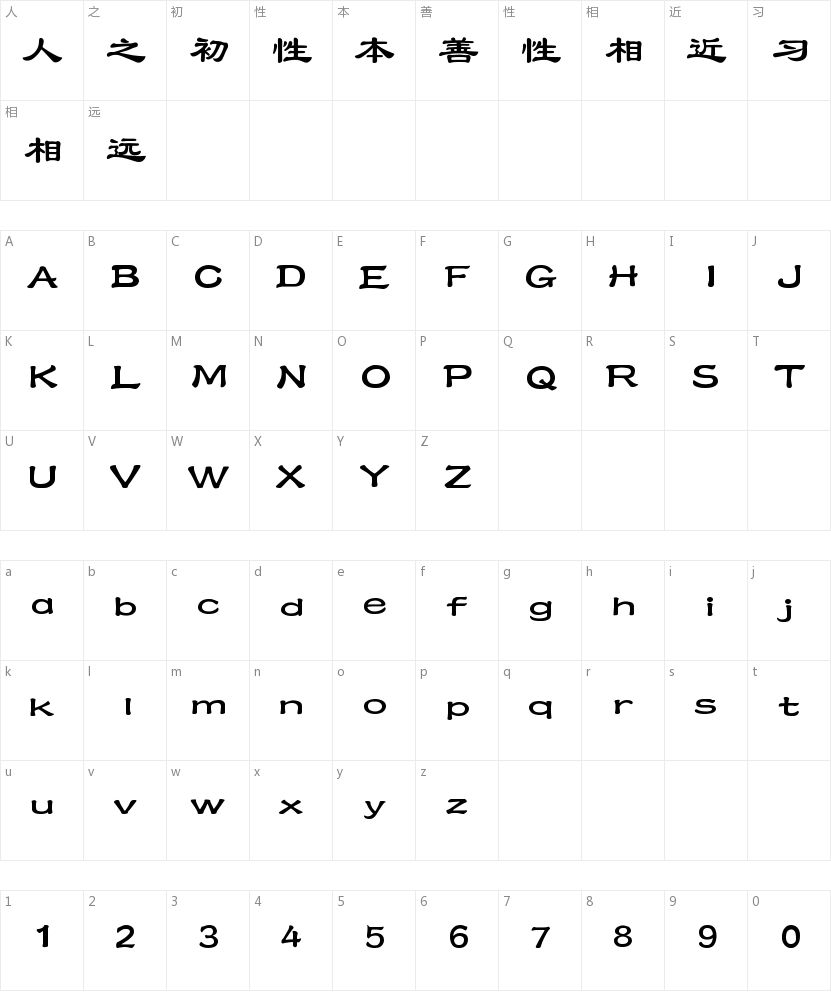
长城粗隶书体
长城粗隶书体是一种中国古典书法字体,它源于宋代宋体,是一种比较粗糙的字体。字体特点是笔画比较粗,笔画间距比较大,笔画粗细变化较大,笔画起伏较大,可以表达出浓郁的古典感觉。长城粗隶书体有着极高的艺术价值,是中国书法艺术的重要组成部分,在中国文化中占据着重要的地位。
长城粗隶书体是一款非常不错的手写艺术字体,具有很好的视觉感,适合于文化类的宣传设计、商业类品牌的广告和产品包装设计以及个性化文字排版等较多场景。